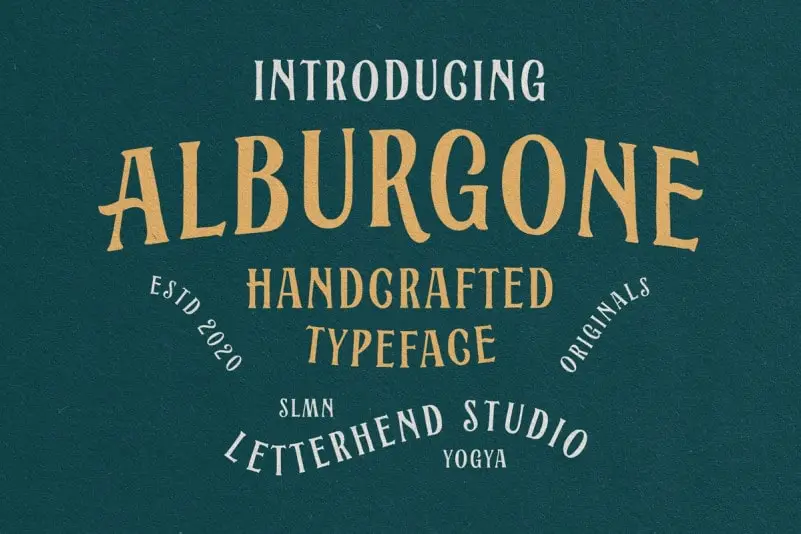
A Alburgone Display Font é uma fonte Lombardica composta por letras maiúsculas, criada para ser mais acessível e intuitiva. Inspirada em postagens de redes sociais e livros de letras, essa fonte foi projetada pela Letterhend Studio como um tipo de letra que remete a memórias nostálgicas. Seu design cuidadoso e detalhado a torna perfeita para aplicações diversas, especialmente em logotipos, convites formais, etiquetas, capas de livro, cartões de aniversário ou casamento, embalagens, roupas, notas de gravata, livros, selos ou qualquer tipo de propósito publicitário. Essa fonte traz uma atmosfera encantada e moderna para seus projetos gráficos, tornando-a um recurso indispensável no seu leque de ferramentas digitais.